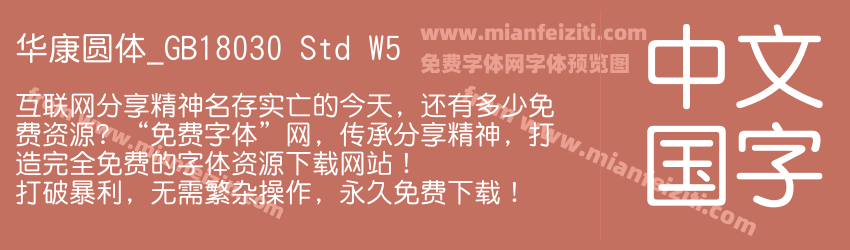
华康圆体_GB18030 Std W5
字体名称: 华康圆体_GB18030 Std W5
Postscript名称: DFYuanW5Std-GB18030
字体版本: Version 3.00 March 3, 2018
本款“华康圆体_GB18030 Std W5”是一款书写很新颖的字体,字体大方,适合各种设计作品使用!欢迎下载!